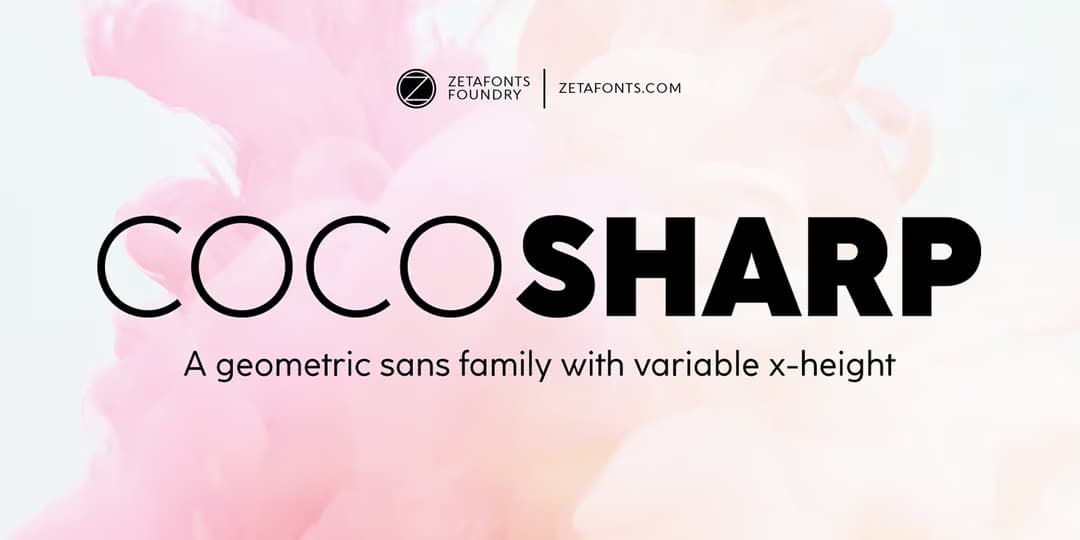
Coco Sharp
本日はかのココ・シャネル Coco Chanel の誕生日(1883)ということでこちら。8年前に紹介した Coco Gothic のリファイン版らしい。名前の通りシャープなジオメトリックサンセリフだが、鬼のような拡張が施されており、スモールキャップスや各種数字はもちろん、ギリシャ文字やキリル文字、果てはアラビア文字までサポートしていて、グリフ数は2000を超える。また小文字の大きさ(xハイト)もレギュラーの他に XS, S, L, XL があって、もちろんそれぞれにイタリックもあって6ウェイトずつで計60種、さらにはバリアブルもアップライトとイタリック2種ある。すんごいビッグファミリー。